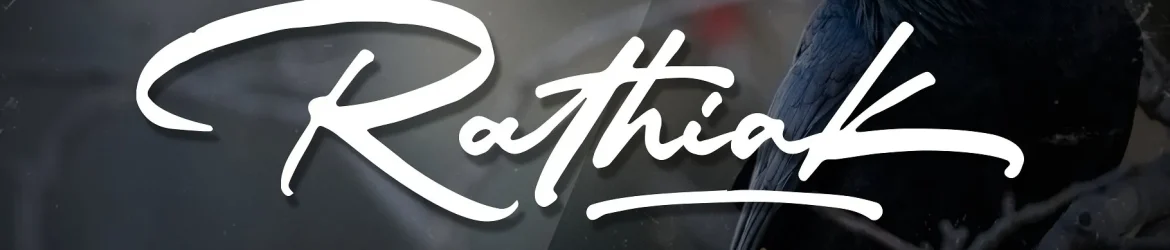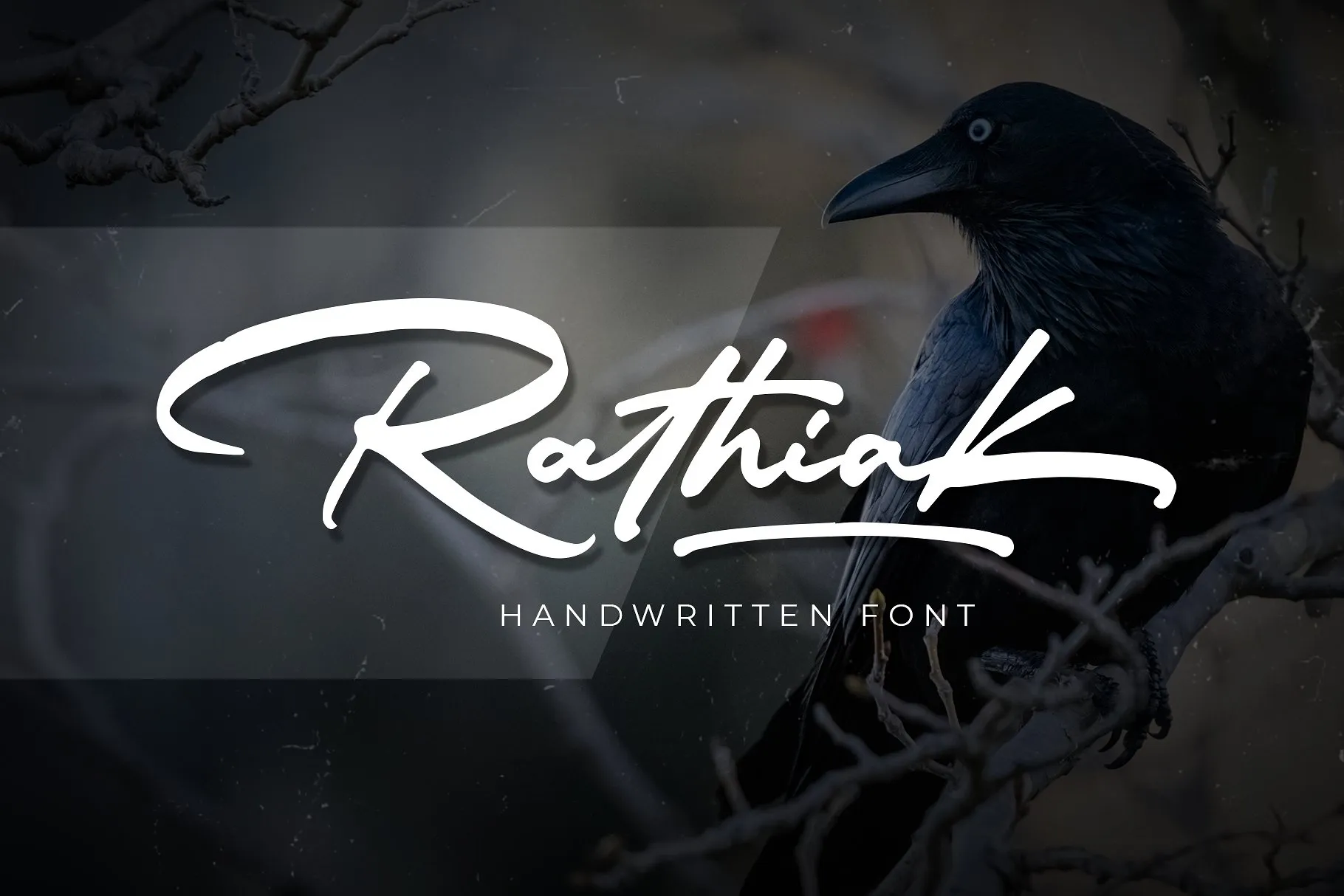
Rathiak Handwritten Font – Fonte Grátis
Rathiak Handwritten Font
A Rathiak Font é uma escolha excelente para aqueles que procuram uma fonte escrita a mão com poder e poder. Ela foi criada por SusiType e apresenta um estilo de letra rústica, chamado de “handwritten font”, ou fonte escrita a mão. Com sua sensibilidade orgânica em cada caractere, esta fonte inclui alternativas e ligaturas que adicionam profundidade e complexidade ao texto impresso. É perfeita para qualquer projeto gráfico, adequada tanto para estilos vintage quanto para o mundo da moda e marca. Suas variedades de escrita a mão deslumbrantes, chamadas de “swash font”, tornam ela ainda mais versátil. Ideal tanto para projetos de impressão como aqueles digitais, a Rathiak Font é um recurso valioso para designers que buscam adicionar um toque único e autêntico às suas criações. Se você está à procura de uma fonte poderosa para sua próxima projeto, não perca tempo. A Senella é versátil o suficiente para qualquer necessidade design, então aproveite esta oportunidade.